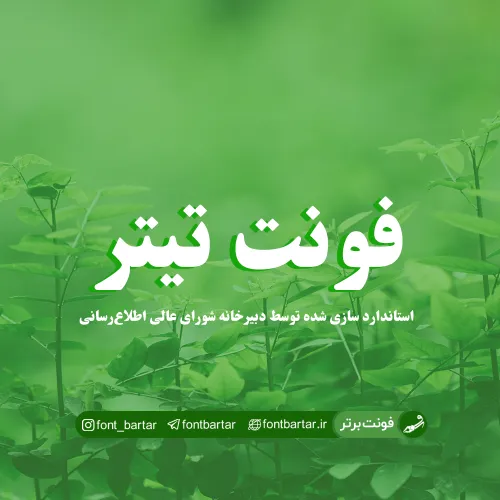
فونت فارسی تیتر
دانلود فونت فارسی تیتر تایپ عربی و فارسی با کیفیت بالا و فرمت ttf مناسب برای استفاده در کارهای گرافیکی و تبلیغاتی که میتوانید از این لحظه آن را از سایت فونت برتر دانلود نمایید.
فونت تیتر مورد استفاده برای:
- طراحان وب سایت و گرافیست های خلاق می توانند از این مجموعه زیبا فونت در طراحی پروژه های تبلیغاتی و تجاری خود کمک بگیرند.